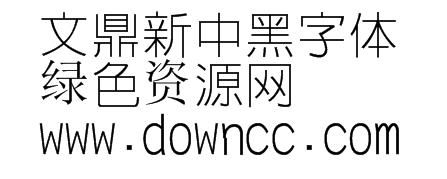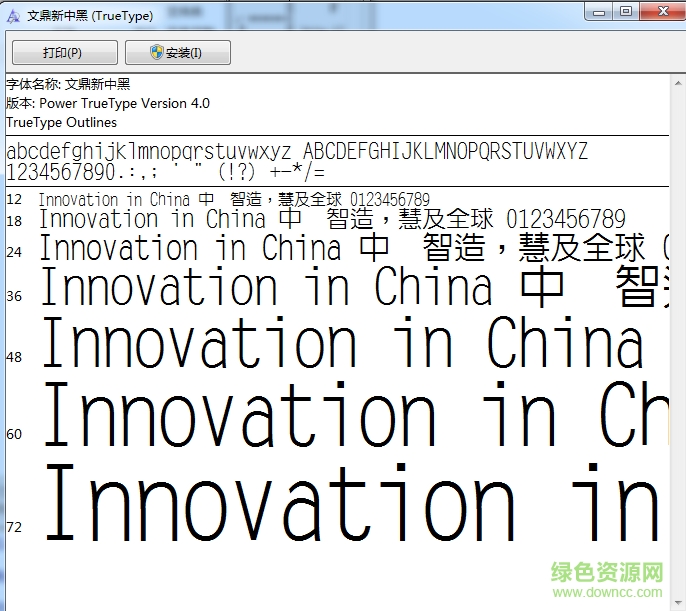
文鼎新中黑是一款簡(jiǎn)潔明亮的文鼎字體,造型簡(jiǎn)約端正,給你清晰的視覺(jué)呈現(xiàn),支持繁簡(jiǎn)體輸入,喜歡的朋友在綠色資源網(wǎng)就可以免費(fèi)下載啦!
文鼎新中黑字體簡(jiǎn)潔干練,文鼎中黑系列的全新字體,支持繁體中文和簡(jiǎn)體中文,可廣泛運(yùn)用于海報(bào)設(shè)計(jì)、名片設(shè)計(jì)、LOGO設(shè)計(jì)等場(chǎng)合。